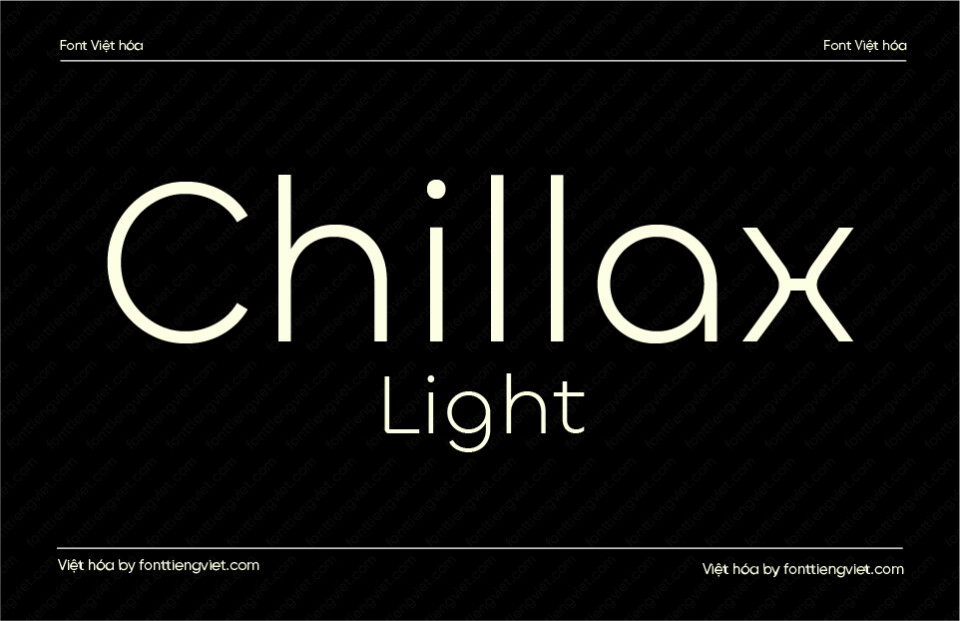
Font Việt hóa 1FTV VIP Chillax Light
Trong thế giới thiết kế đồ họa ngày nay, việc lựa chọn một bộ Font Miễn Phí chất lượng luôn là ưu tiên hàng đầu của các bạn học sinh và sinh viên. Đặc biệt, mẫu Font Việt hóa 1FTV VIP Chillax Light đang trở thành cơn sốt nhờ vẻ đẹp thanh mảnh, tinh tế và vô cùng hiện đại. Đây không chỉ là một công cụ trình bày văn bản thông thường mà còn là nguồn cảm hứng giúp các bạn trẻ tự do sáng tạo trong các bài thuyết trình hay dự án cá nhân tại nhà trường. Với sự phát triển của công nghệ, việc sở hữu những bộ chữ đã được tinh chỉnh dấu tiếng Việt chuẩn xác giúp người dùng tiết kiệm thời gian và đảm bảo tính thẩm mỹ cao nhất cho mọi sản phẩm thiết kế đồ họa chuyên nghiệp.
Sức hút của bộ Font Việt hóa 1FTV VIP Chillax Light trong thiết kế
Lý do khiến Font Việt hóa 1FTV VIP Chillax Light nhận được sự yêu mến nồng nhiệt chính là cấu trúc hình học tối giản. Những đường nét của bộ chữ này được gọt giũa mềm mại, tạo cảm giác thư thái đúng như tên gọi Chillax của nó. Đối với các bạn học sinh, việc sử dụng font chữ này trong các bài thiết kế báo tường điện tử hoặc làm tiêu đề cho các slide thuyết trình sẽ giúp nội dung trở nên dễ đọc và bắt mắt hơn. Sự nhẹ nhàng của biến thể Light giúp không gian thiết kế có thêm những khoảng thở cần thiết, tránh gây cảm giác nặng nề cho người xem.
Đặc điểm nổi bật của kiểu chữ 1FTV VIP Chillax Light
Bộ chữ này nổi bật với khả năng hiển thị sắc nét trên cả màn hình kỹ thuật số và các ấn phẩm in ấn. Các ký tự tiếng Việt được thiết kế tỉ mỉ, đảm bảo các dấu thanh không bị dính vào chữ hay gây rối mắt. Điều này cực kỳ quan trọng đối với các bạn đang học tập trong môi trường sư phạm, nơi yêu cầu sự chuẩn mực về mặt ngôn ngữ. Ngoài ra, tính ứng dụng đa dạng từ làm thiệp chúc mừng, thiết kế bìa sách cho đến trang trí các trang mạng xã hội cá nhân đã giúp mẫu chữ này chiếm trọn niềm tin của cộng đồng người dùng yêu thích nghệ thuật chữ viết tại Việt Nam.
Cách ứng dụng Font Việt hóa 1FTV VIP Chillax Light hiệu quả
Để phát huy tối đa vẻ đẹp của Font Việt hóa 1FTV VIP Chillax Light, bạn nên kết hợp nó với những tông màu pastel hoặc các nền ảnh tối giản. Trong các dự án học đường, hãy thử dùng font này cho các phần trích dẫn quan trọng hoặc lời ngỏ để tạo điểm nhấn thanh lịch. Do đặc tính mảnh mai, bộ chữ này sẽ hoạt động tốt nhất khi được đặt ở kích thước vừa và lớn. Nếu bạn muốn tạo ra một bố cục phân cấp rõ ràng, hãy phối hợp nó cùng các phiên bản đậm hơn trong cùng gia đình font để tạo sự đồng nhất nhưng vẫn đầy cá tính cho tác phẩm của mình.
Kết luận về bộ chữ 1FTV VIP Chillax Light